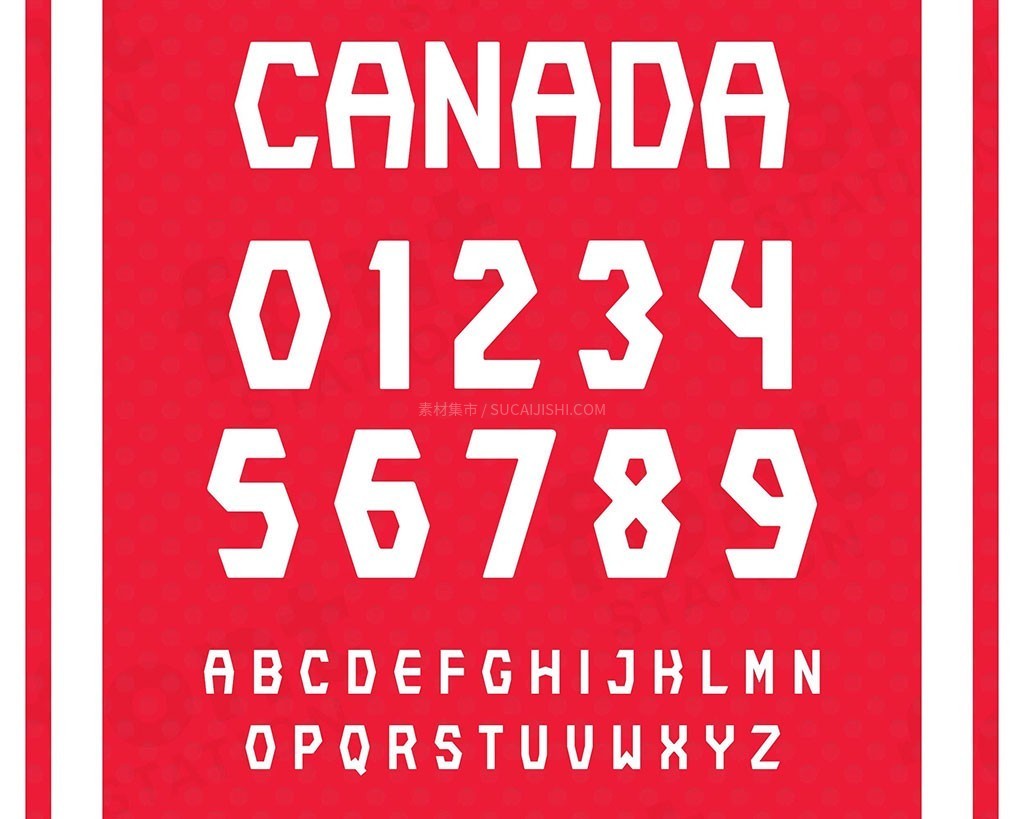
加拿大2022世界杯球衣号码字体
这套字体是 2022 年卡塔尔世界杯加拿大国家队官方使用的专属号码字体。其设计灵感源于加拿大自然景观与现代体育精神的融合,采用几何无衬线风格,笔画粗犷且带有独特的圆角切割工艺。该字体具备极高的辨识度与力量感,非常适合用于体育海报设计、足球周边周边开发及数字艺术创作。